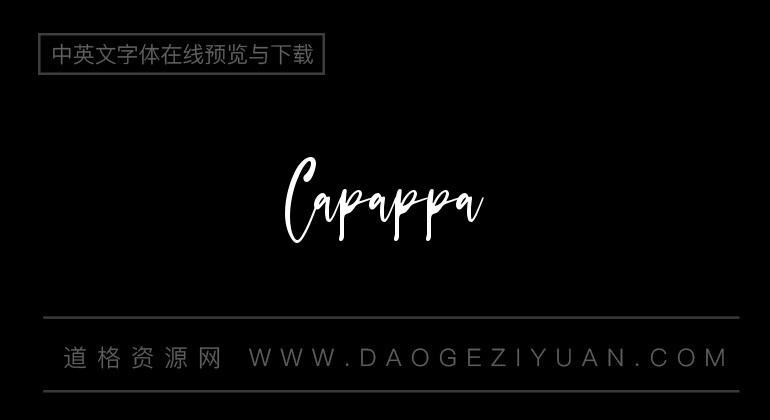
Capappa 字体是一款现代感十足的英文字体,它的特点是拥有清晰的结构,细节处理得非常到位,大小写字母的设计比较统一,它的笔画比较粗细,比较容易识别,具有良好的可读性。Capappa 字体被广泛应用在平面设计、UI设计、图标设计等领域,可以为你的设计增添不一样的视觉效果。内容介绍
Capappa是一款非常不错的手写艺术字体,具有很好的视觉感,适合于文化类的宣传设计、商业类品牌的广告和产品包装设计以及个性化文字排版等较多场景。